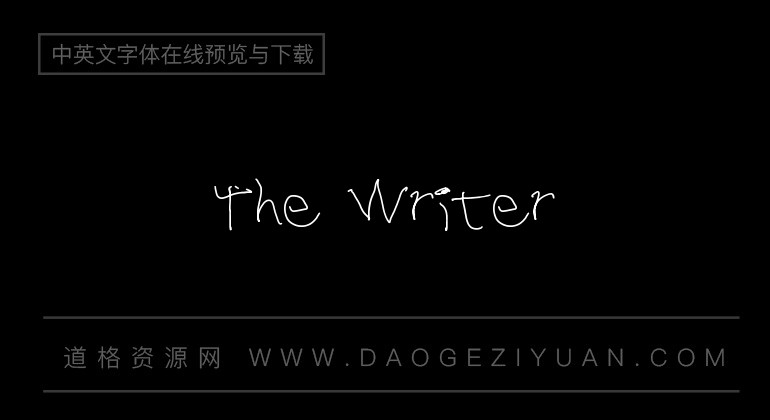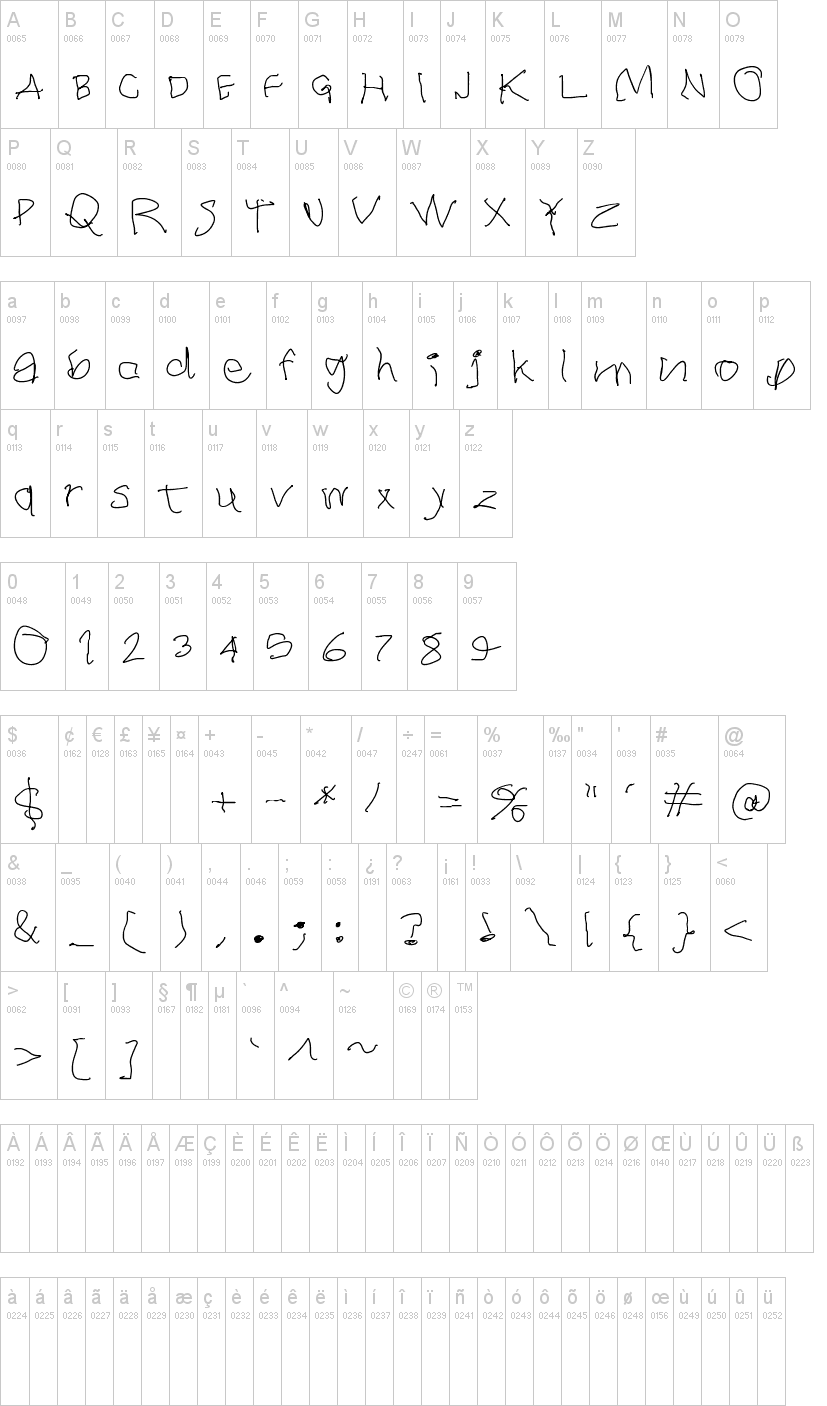
The Writer 是一種手寫風格的字體,具有非常自然和有機的外觀。它的筆劃看起來像是由簡單的圓曲線和銳利的直線組成的,這使得它看起來既流暢又清晰。此外,它的筆劃粗細變化非常自然,彷彿是由真實的手寫字體生成的。 The Writer 字體適合用於許多不同的設計項目,例如海報、標誌、卡片和其他文本設計。它使得文本看起來非常富有個性,並且可以突出品牌或個人的獨特風格。內容介紹
The Writer是一款非常不錯的手寫藝術字體,具有很好的視覺感,適合於文化類的宣傳設計、商業類品牌的廣告和產品包裝設計以及個性化文字排版等較多場景。